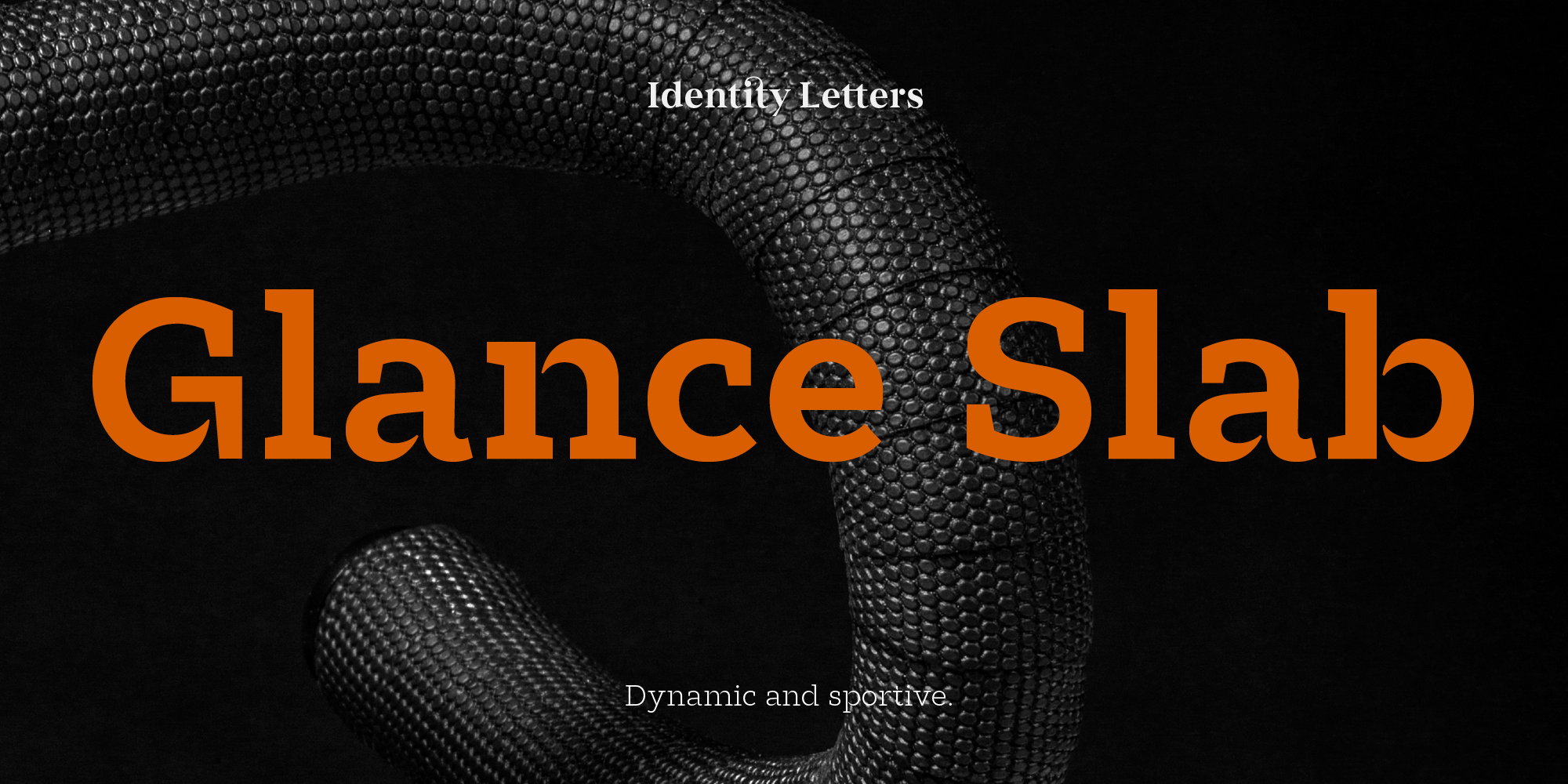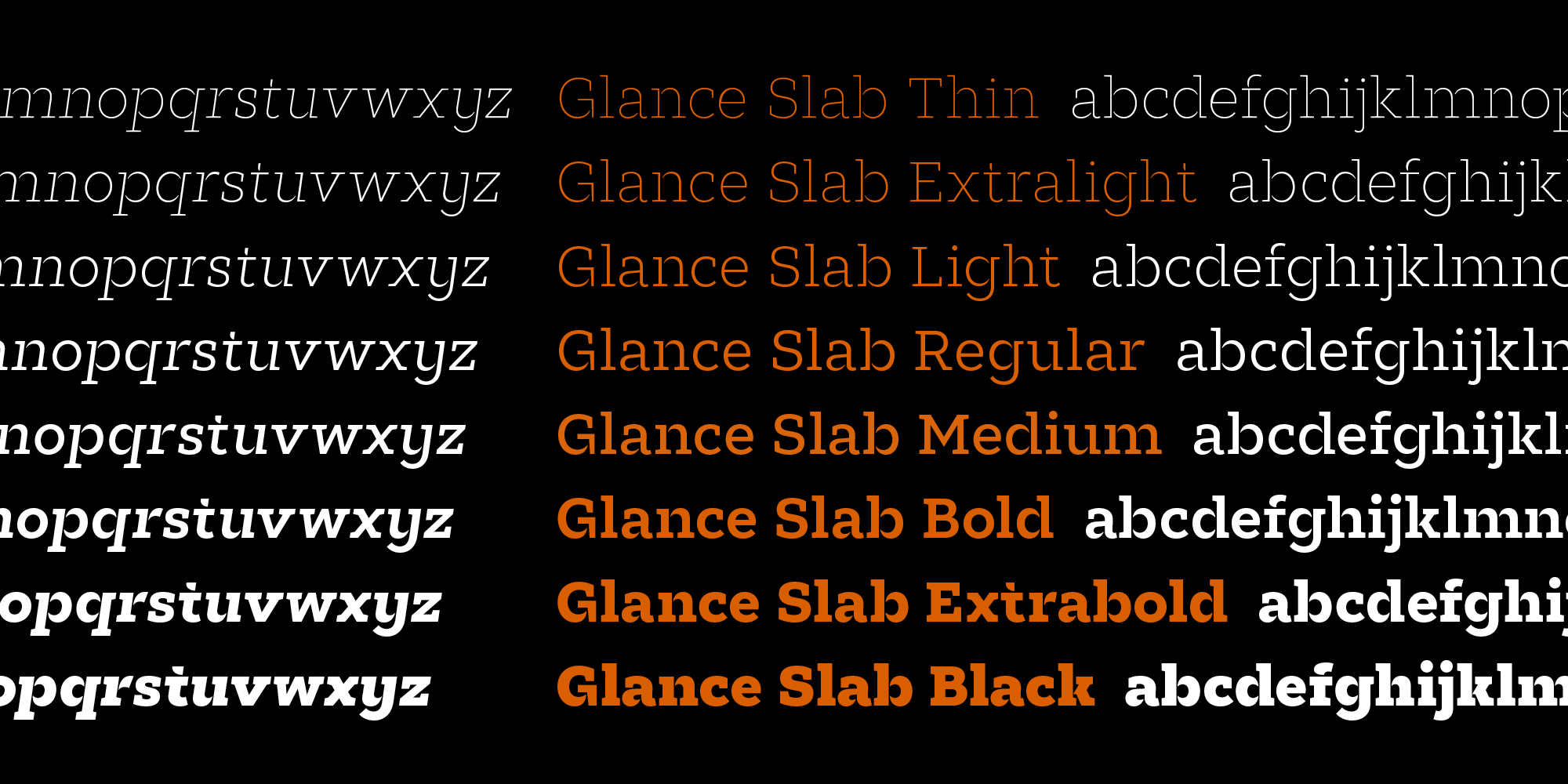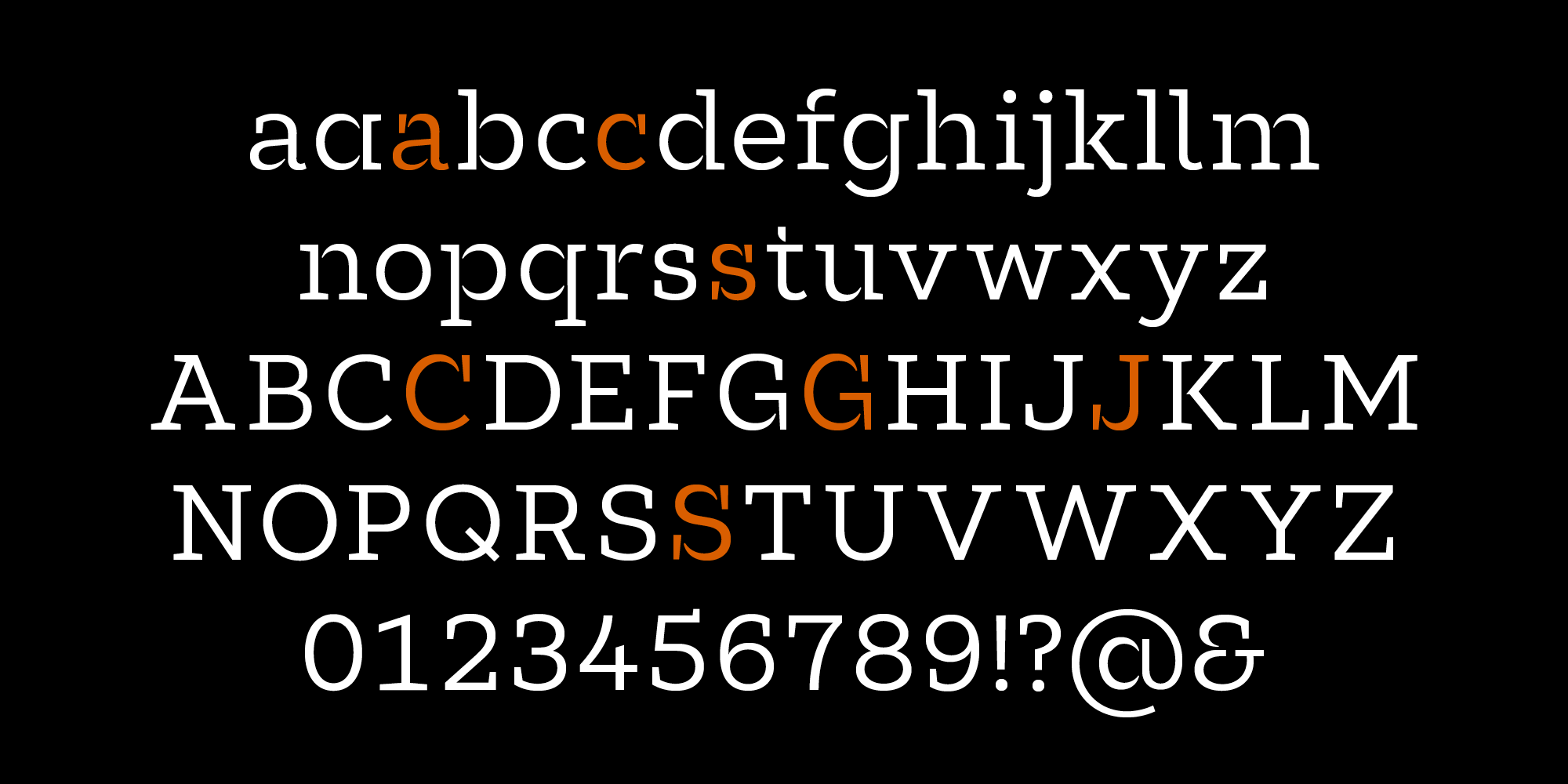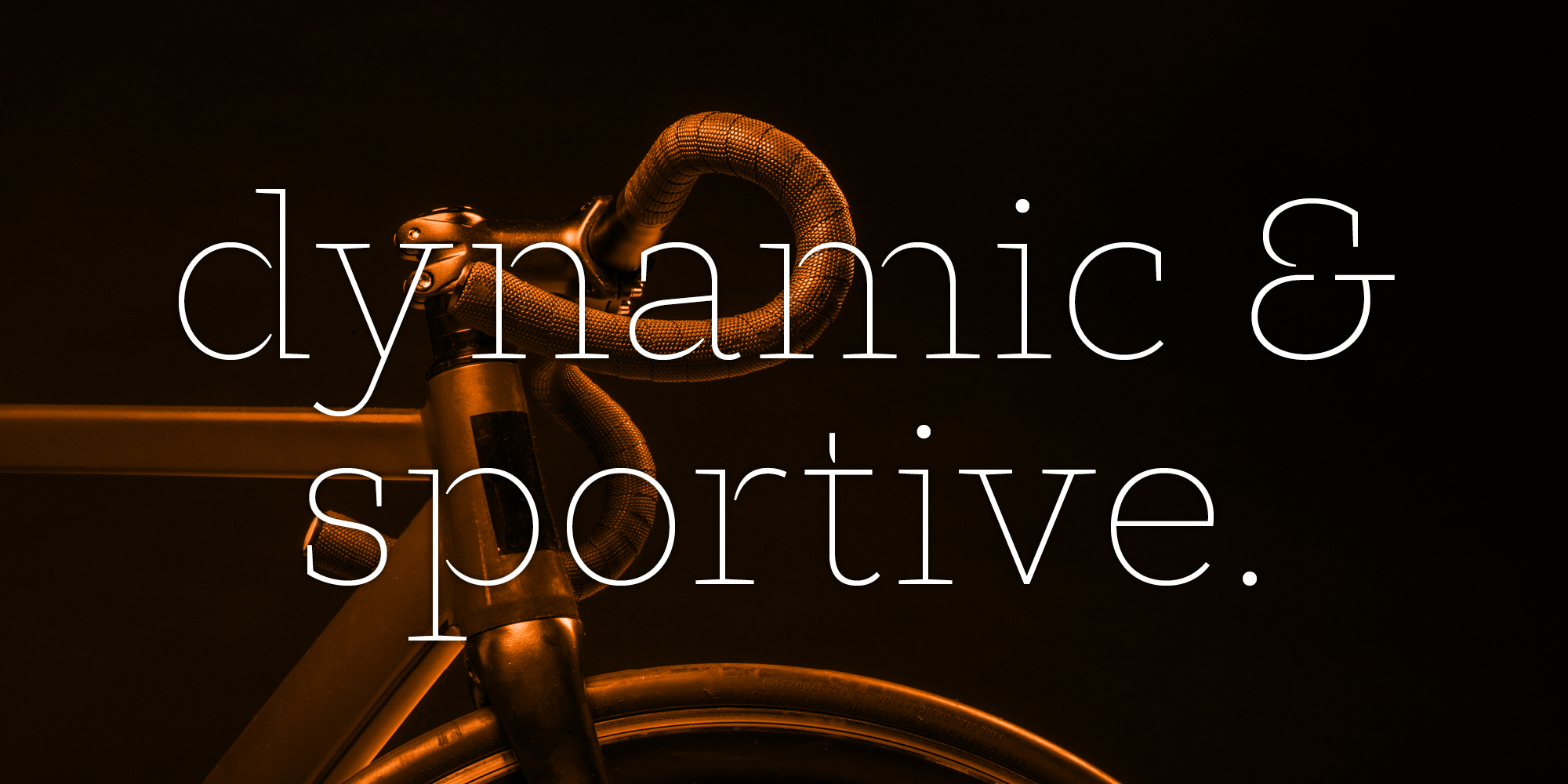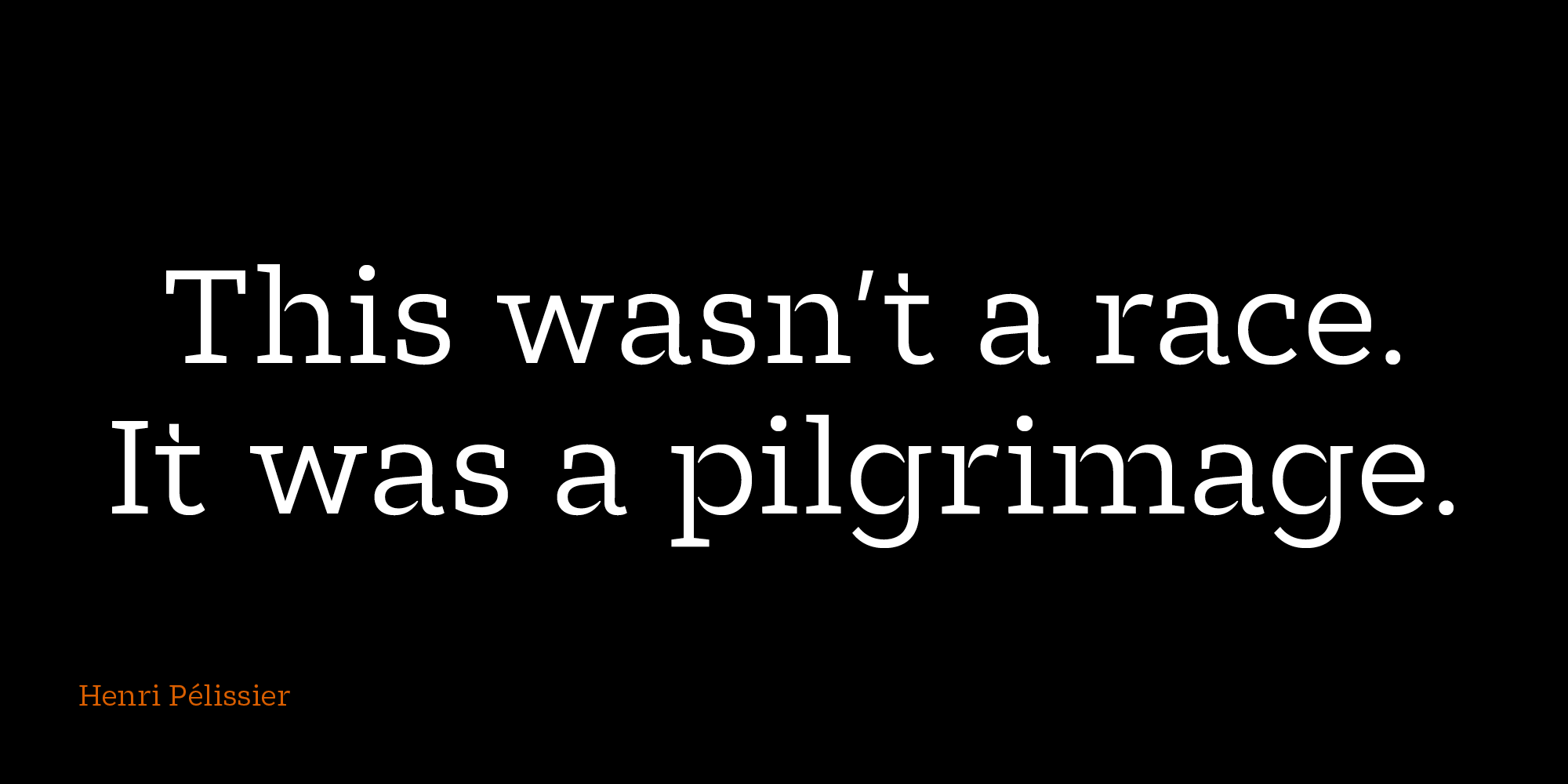
• Serifen:
• slab
• Antiqua geometrisch
• Versaleszett:
• enthalten
Glance Slab ist eine dynamische und sportliche Slab Serif. Die Schrift ist durch nicht verbundene Slab-Serifen geprägt. Die von Moritz Kleinsorge entworfene Glance Slab besteht aus acht Strichstärken von Thin bis Black, in Roman und Italic. Jeder Stil ist mit einem Zeichensatz von etwa 730 Glyphen ausgestattet, welcher (schwarz) eingekreiste Ziffern und Pfeile, Ligaturen, eine erweiterte Sprachunterstützung und vieles mehr enthält.